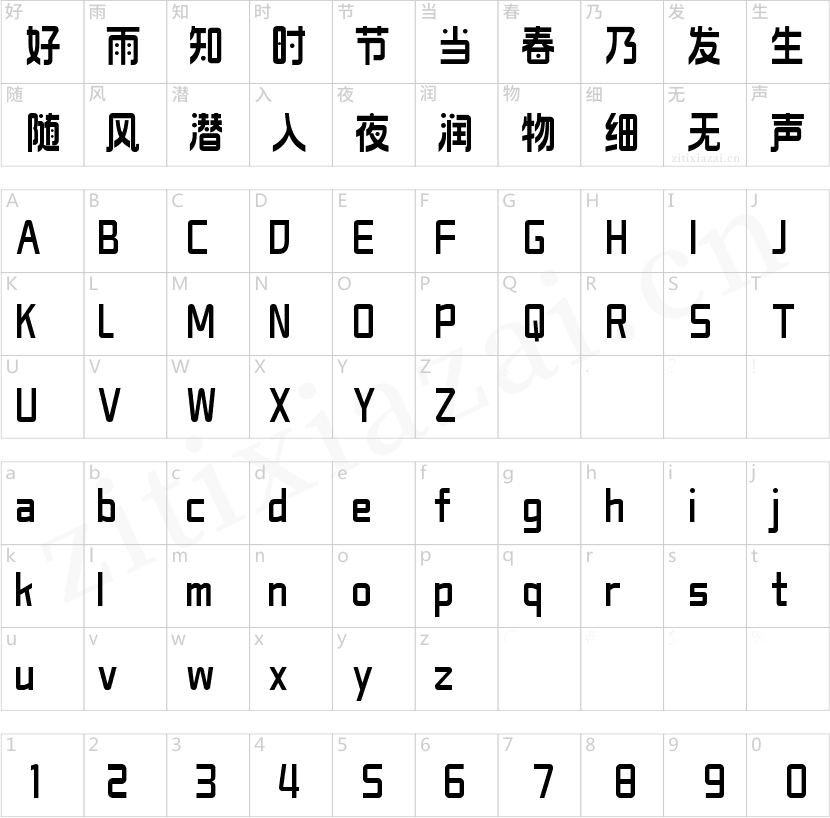
字小魂闲趣体
字小魂闲趣体是一款艺术字体,深受广大设计师的喜爱。
字体设计说明
字魂字体字小魂闲趣体字体是由字魂创意字库设计并生产的一款可商用的字体,被收录于字小魂系列。该字体支持GB-2312标准,包含6942个中文、字母、符号和数字,字体类型偏向黑体,具有简约的风格,在市面上广泛用于企业文化、晚会年会、视频综艺等场景。